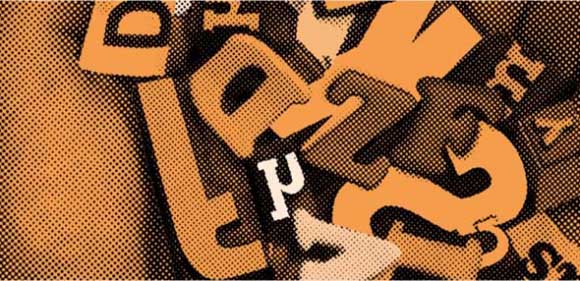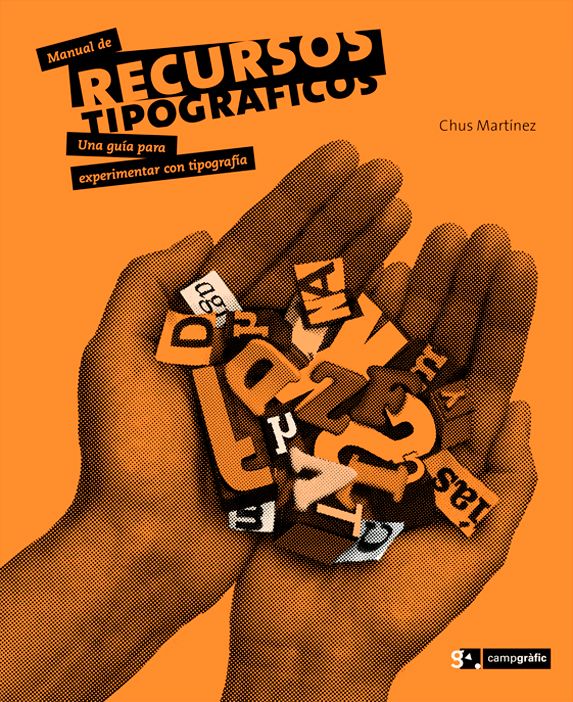
La editorial Campgràfic nos tiene acostumbrados a ediciones de los mejores textos clásicos sobre tipografía, su historia y su práctica. En esta ocasión os presentamos un estupendo compendio de tipografía práctica. Se trata de Manual de recursos tipográficos y esta escrito por la diseñadora gráfica y profesora titular de la Escola d’Art i Superior de Disseny de València Chus Martínez.
A través de una serie de ejemplos articulados en torno a una clasificación ordenada de los recursos que nos ofrece la tipografía, el libro nos acompaña por diferentes soluciones gráficas para, a continuación en una segunda parte práctica, proponer una extensa paleta de ejercicios con los que experimentar los recursos anteriormente expuestos. El objetivo es evidente, y consiste en potenciar la sensibilidad hacia las formas tipográficas y su potencial como imagen.
La tipografía abarca un amplio campo dentro de la enseñanza reglada del diseño gráfico y la comunicación. Su dualidad como transmisora de mensajes tanto en la forma verbal como gráfica la convierten en una herramienta básica del diseñador. Ser capaces de explorar toda su potencialidad a través de una obra en la que podemos encontrar de forma ordenada los recursos que podemos utilizar, hacen de Manual de recursos tipográficos un libroimprescindible tanto para estudiantes como para docentes.
Manual de recursos tipográficos
Chus Martínez